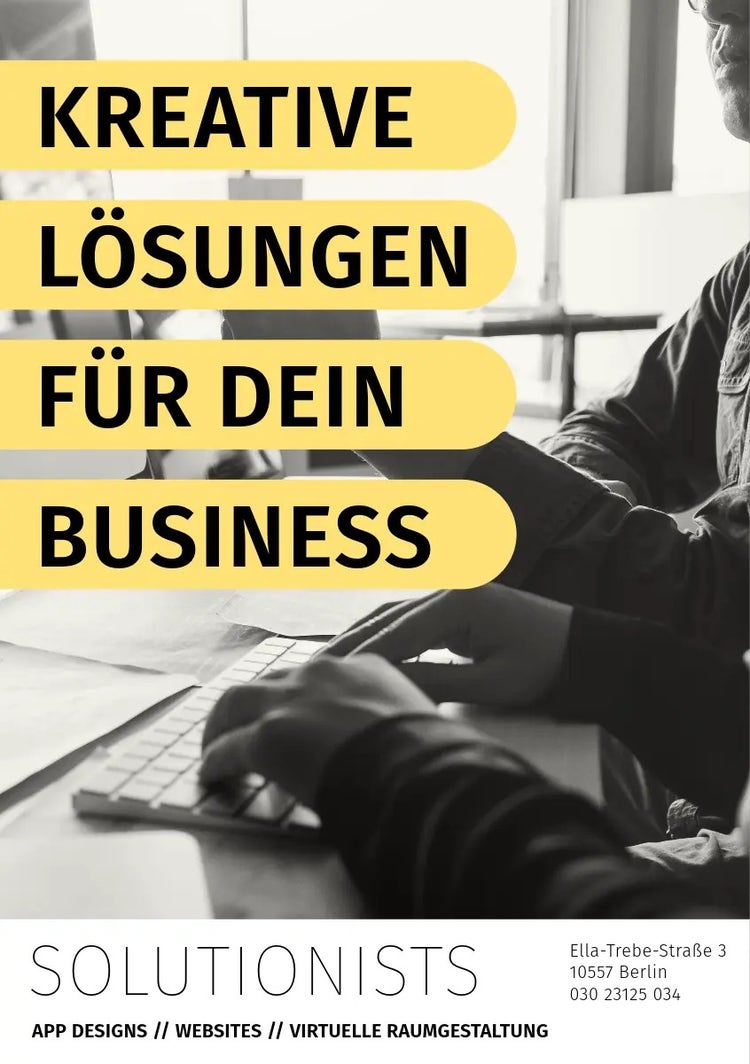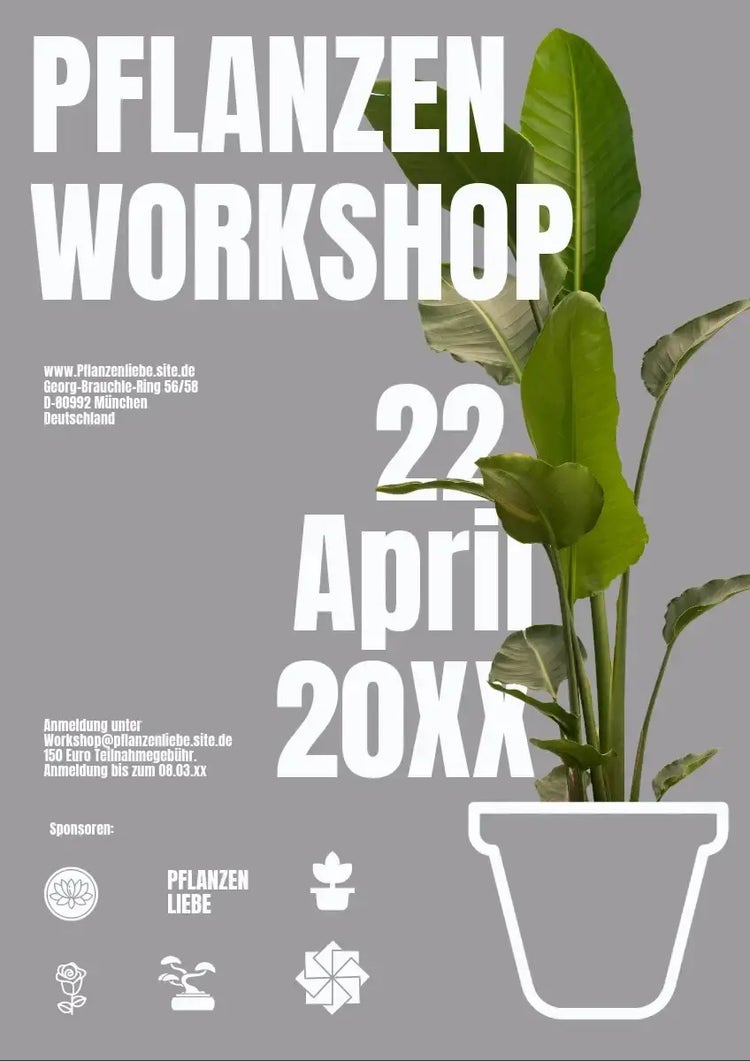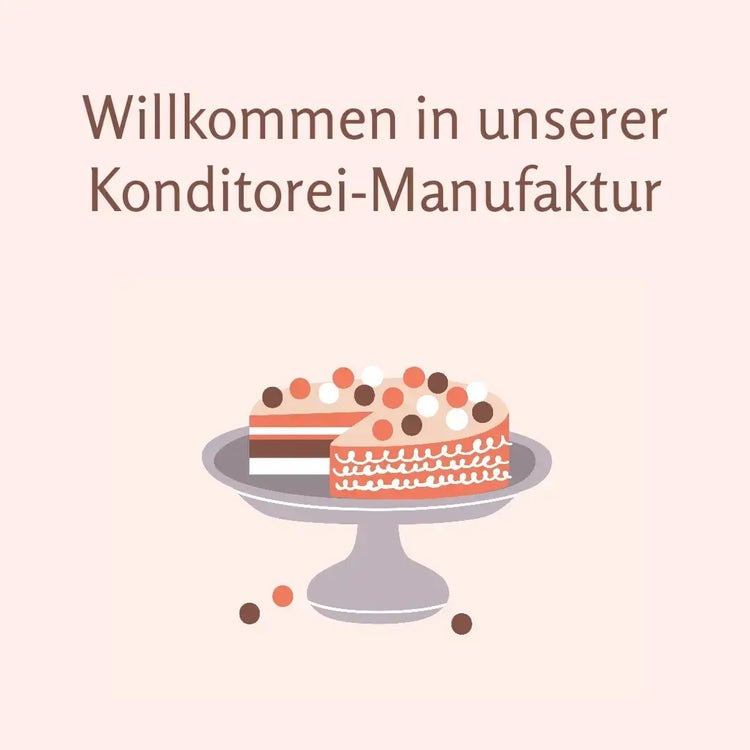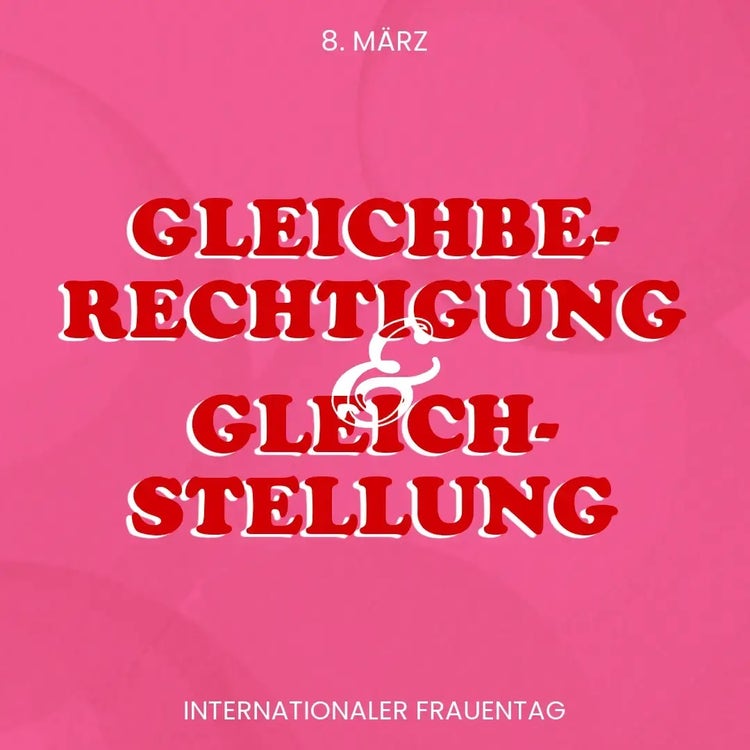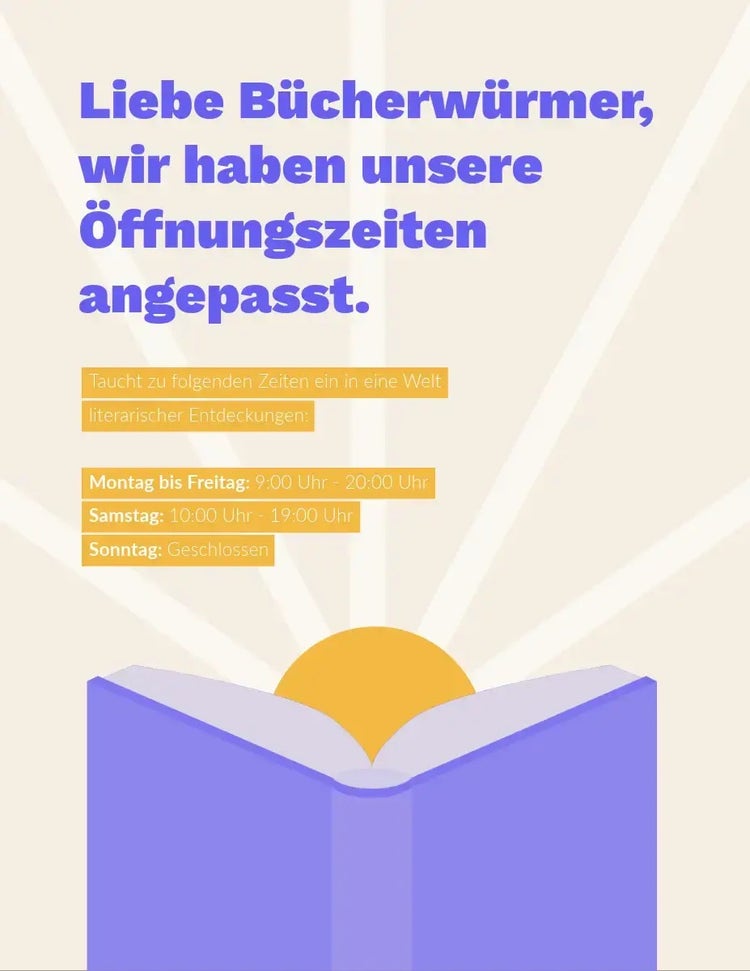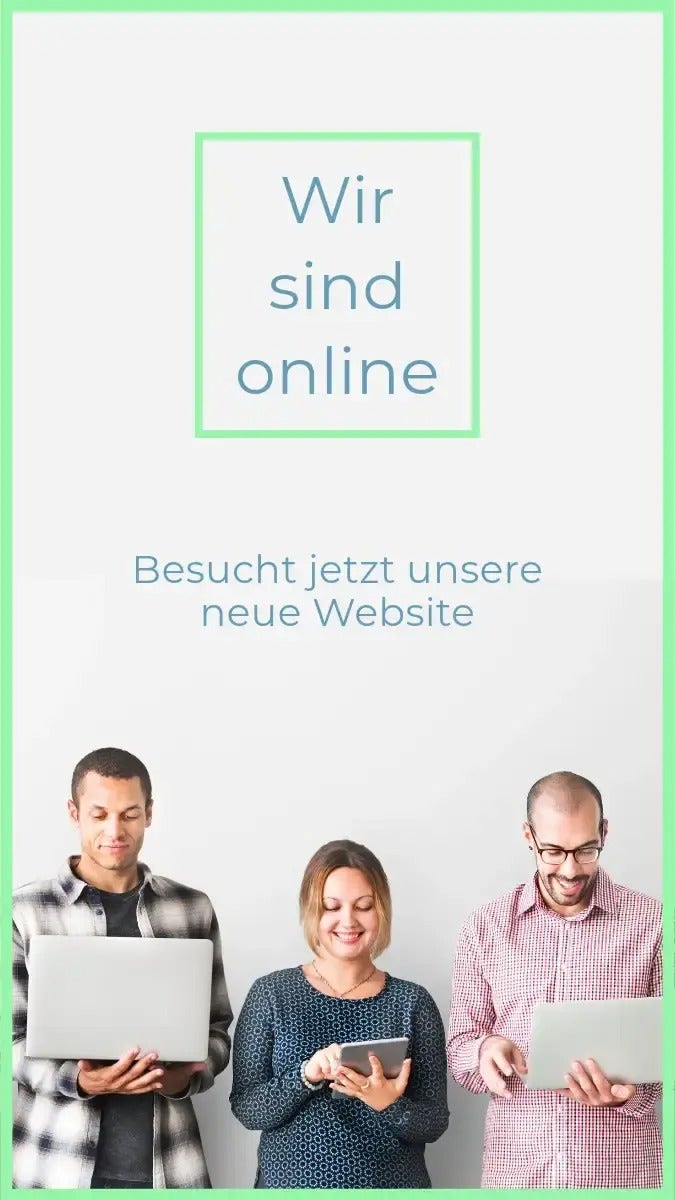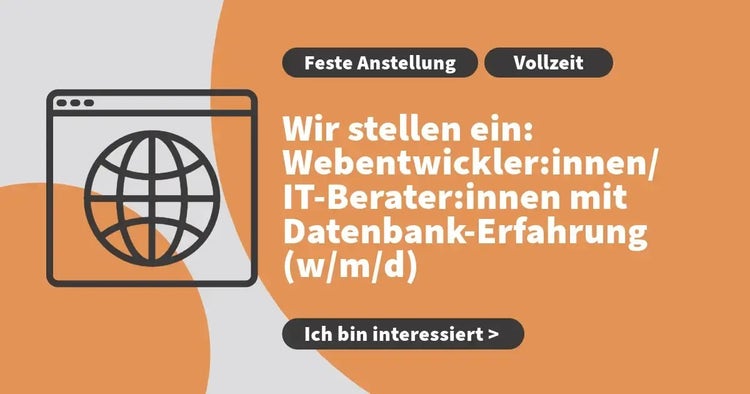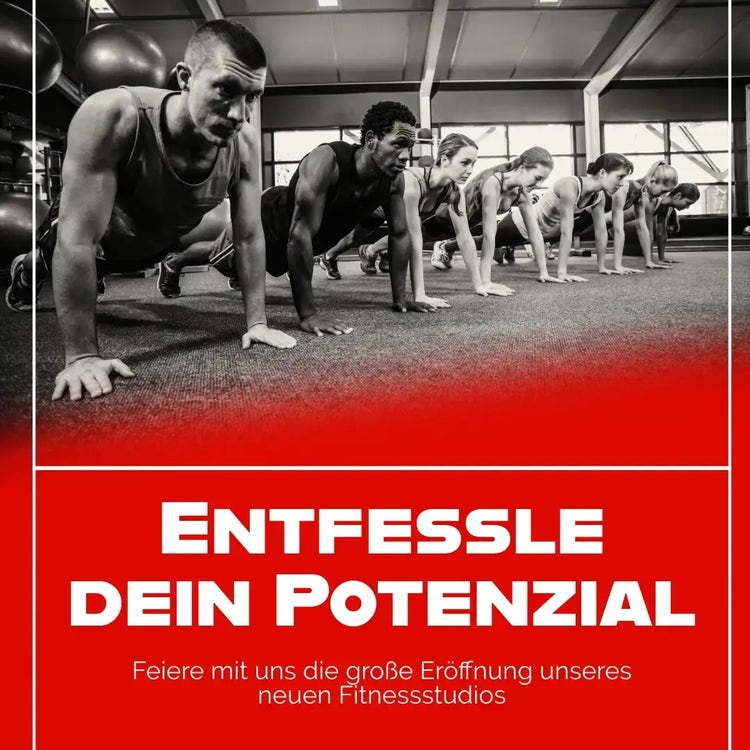
Die besten professionellen Schriftarten für deine Webseite: Tipps für ein modernes Website-Design.
Entdecke die besten professionellen Schriftarten für deine Webseite.
Webdesign wird immer wichtiger. Wir vernetzen uns mit unseren Freunden online, shoppen und verlieben uns über das Internet. Wir suchen Häuser aus, in denen wir leben wollen, informieren uns über Hobbies und Nachrichten. Das Internet und seine Webseiten sind für das heutige Leben essenziell geworden. Die richtige Schriftart ist dabei nicht nur ein funktionales Element, sondern bestimmt maßgeblich das Erscheinungsbild der Webseite und trägt wesentlich zur Benutzererfahrung bei.
Dabei wird der Wettbewerb immer größer und oft sind es kleine Details, die den entscheidenden Unterschied machen. Ein professionelles und ästhetisches Design hilft dabei, sich von der Masse abzuheben und trotzdem Vertrauen beim Kunden zu erwecken.
Die Bedeutung von professionellen Schriftarten.
Schriftarten spielen eine entscheidende Rolle im Webdesign und bestimmen oftmals das gesamte Erscheinungsbild. Die Wahl der richtigen Schriftart hat dabei Auswirkungen auf eine Reihe verschiedener Faktoren.
Am Anfang stehen dabei immer die Lesbarkeit und somit auch die Benutzererfahrung. Eine professionelle Schriftart muss gut lesbar sein und eine angenehme Leseerfahrung für den Besucher der Webseite mit sich bringen. Der Inhalt muss schnell zu erfassen sein, denn nur dadurch erhöht sich die Wahrscheinlichkeit, dass der Besucher auch länger auf der Seite bleibt.
Dies trägt auch maßgeblich zur Glaubwürdigkeit und Professionalität der Seite bei. Mit einem ästhetischen und gut lesbaren Design wird man ernst genommen. Schriftarten, die stark ablenken, wie eine Handschriftart, wirken schnell unprofessionell und sind auch schlecht lesbar.
Dabei sollte sich die Schriftart konsistent durch das Erscheinungsbild der Marke ziehen. Die Verwendung konsistenter Schriftarten in allen Bereichen deiner Webseite, von Überschriften bis hin zu Fließtexten, hilft dabei, deine Botschaft klar und konsistent zu kommunizieren.
Dies kann auch ein Punkt sein, um sich von der Konkurrenz abzuheben. Ein unverwechselbarer eigener Stil kann Teil des Brandings sein und Assoziationen bei der Zielgruppe auslösen.
Wichtig ist jedoch auch, dass man darauf achtet, dass sich die Schriftart an unterschiedliche Displaygrößen gut anpassen lässt. Die Webseite sollte auf einem PC genauso gut lesbar sein wie auf einem Smartphone mit einem kleinen Display. Die Wahl der richtigen Schriftart ist ein wichtiger Schritt, um eine benutzerfreundliche und professionelle Webseite zu gestalten.
Entdecke die perfekte Schriftart für deine Webseite.
Auswahlkriterien für professionelle Schriftarten.
Die richtige Schriftart zu finden kann manchmal Zeit in Anspruch nehmen, denn es gibt viele Kriterien, die davon abhängen.
• Lesbarkeit: Höchsten Anspruch hat die Lesbarkeit. Der legendäre Font “Wingdings” ist dafür bekannt, unlesbar zu sein und sollte zum Beispiel nicht genutzt werden. Aber auch kursive Handschriften sind für einen Fließtext nicht die beste Wahl, da man länger braucht, um sie zu lesen.
• Stil und Ästhetik: Sie sind dabei ein weiterer wichtiger Punkt, denn sie spiegeln das Image und die Werte wider. Die Schriftarten sollten zum Gesamtdesign der Webseite und der Marke dahinter passen. Ein konsistentes visuelles Erscheinungsbild ist entscheidend für eine starke Markenidentität.
• Vielseitigkeit: Die Schriftarten sollten vielseitig einsetzbar sein. Dazu zählen Überschriften, Fließtext, Menüs und auch Call to Action Elementen. Vielseitige Schriftarten ermöglichen eine flexiblere Gestaltung und bieten mehr Möglichkeiten für kreative Layouts.
• Lizenzen: Einige Website Design Templates funktionieren nur mit der entsprechenden Schriftart, da diese im Mittelpunkt steht. Überprüfe vorher, ob der Font in dem Template für die gewerbliche Nutzung geeignet ist und ob es möglich ist, diese Schriftart auch in einem anderen Content Management System zu nutzen.
• Sprachen: Wenn deine Webseite in verschiedenen Sprachen dargestellt werden soll, solltest du überprüfen, ob die Schriftart auch Sonderzeichen von anderen Sprachen enthält, um eine optimale Lesbarkeit in verschiedenen Sprachen zu gewährleisten.
Schau dir die besten Website Design Templates an.
Empfohlene professionelle Schriftarten für Webseiten.
Es gibt viele unterschiedliche Schriftarten und auch viele sehr professionelle. Auf den meisten Webseiten sieht man jedoch immer die gleichen Fonts, die sich über die Jahre als Best Practice herausgestellt haben, die je nach Anforderung und Stil der Webseite variieren.
Moderne Website-Designs erfordern oft eine hohe Flexibilität und Anpassungsfähigkeit, um den ständig ändernden Anforderungen gerecht zu werden. Die richtige Schriftart bietet dabei eine breite Palette von Stilen, Gewichten und Variationen, die es ermöglicht, verschiedene Designkonzepte zu realisieren und einzigartige visuelle Elemente zu schaffen.
Schriftarten tragen wesentlich dazu bei, ein modernes und ansprechendes Website Design zu schaffen. Benutzererfahrung und Markenimage stehen dabei immer im Vordergrund.